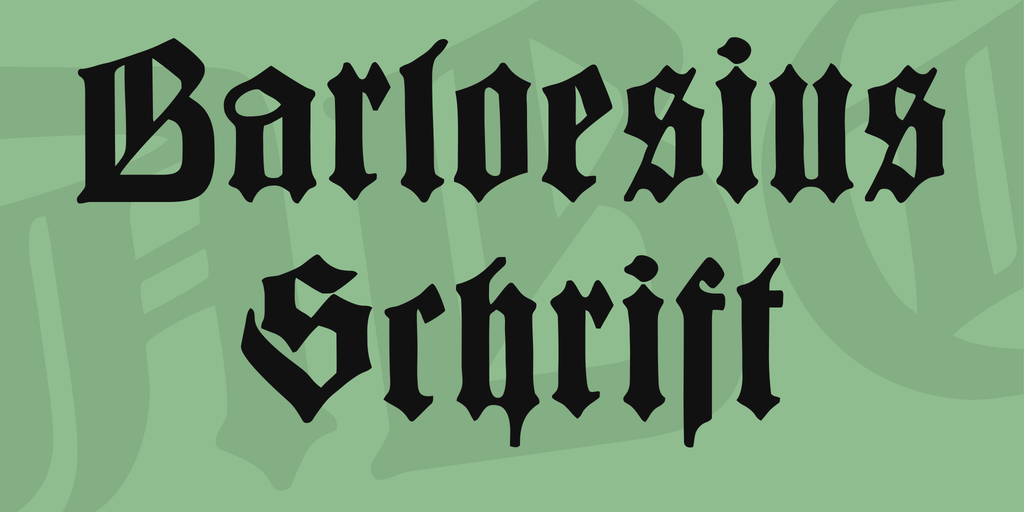
A fonte Barloesius Schrift é uma escolha excepcional para qualquer projeto que deseje capturar atenção com elegância e versatilidade. Desenhada pelo designer georg Barlösius, esta fonte foi lançada pela Bauer foundry em 1906. Não possuímos muitos comentários sobre ela, exceto por ela ser um design inigualável que transmite uma beleza clássica e uma leveção moderna. Este elegante tipo de letras é particularmente adequado para aplicações de display, onde sua simetria e harmonia podem destacar a sua mensagem. Sua estrutura firme e bem planejada proporciona uma escrita profissional e sóbria, enquanto seu tom suave e moderno permite que se adapte com facilidade a diferentes ambientes ou contextos. Ideal tanto para publicações de design gráfico quanto para marcas e identidades visuais criativas, a Barloesius Schrift é uma fonte visualmente atraente que pode ajudar qualquer projeto a brilhar. Sua elegância permanece firme mesmo em textos mais curtos, mantendo sua consistência e precisão – tornando-a um recurso valioso para designers gráficos de todo o Brasil e mundo.